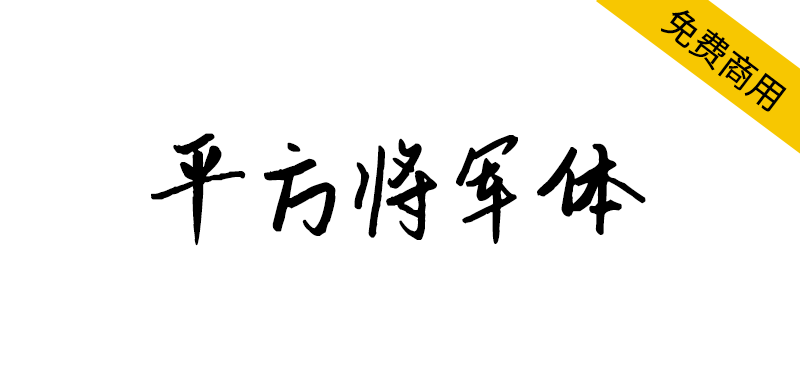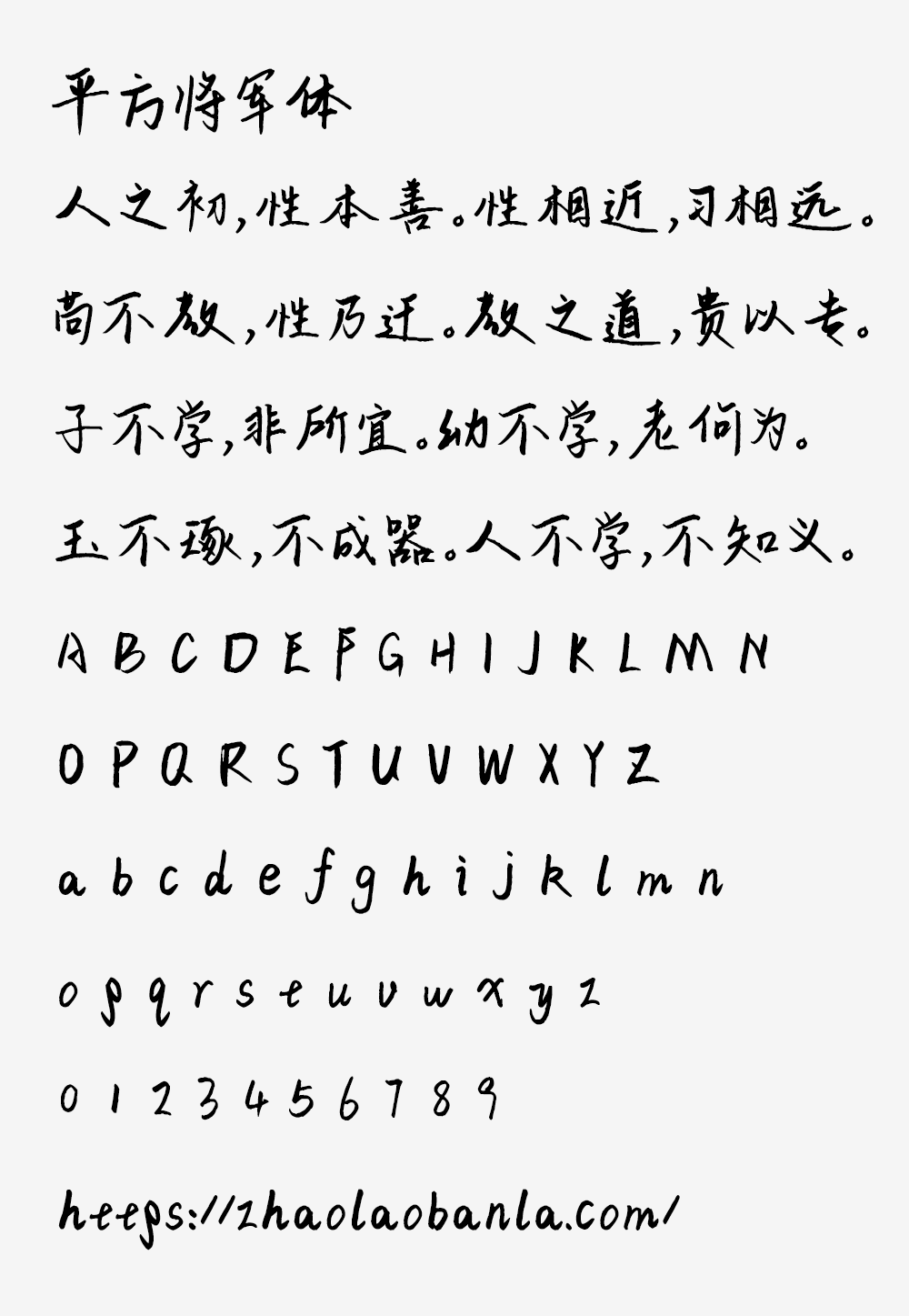
【平方将军体】一款结构端庄大方的创意手写字体
还在为商业设计找不到免费又高级的字体发愁?这款被设计师私藏的「平方将军体」彻底打破困局!笔画匀称如刀削,结构端庄似松柏,既满足广告设计的视觉冲击力,又适合书法练习的笔锋掌控。最关键的是——个人和企业均可免费商用,自媒体、电商设计从此告别版权纠纷。但要注意:商标注册和违法用途被明令禁止!点击了解如何快速获取这款零成本设计利器。
【平方将军体】一款结构端庄大方的创意手写字体
平方江南体是一款创意手写字体,笔画粗细匀称,结构端庄大方,出色的视觉表现力,适用范围广泛,可完美契合平面广告设计以及书法练习等多种使用场景